Trong thiết kế đồ họa, font chữ không chỉ là yếu tố dùng để hiển thị nội dung mà còn góp phần truyền tải cảm xúc, phong cách và cá tính của toàn bộ sản phẩm. Một thiết kế có thể trở nên chuyên nghiệp, sáng tạo và thu hút hơn rất nhiều nếu designer biết lựa chọn font chữ phù hợp. Chính vì vậy, nhu cầu Tải Font Chữ miễn phí ngày càng được nhiều nhà thiết kế, marketer, content creator và chủ shop online quan tâm.
Bộ font chữ đẹp có thể ứng dụng trong nhiều hạng mục khác nhau như thiết kế poster, banner quảng cáo, logo, ấn phẩm truyền thông, bài đăng mạng xã hội, thiệp mời, tiêu đề video, giao diện website hoặc các sản phẩm in ấn. Với designer, việc sở hữu một thư viện font đa dạng sẽ giúp tiết kiệm thời gian sáng tạo, đồng thời mở rộng khả năng biến hóa trong từng dự án thiết kế.
Vì Sao Designer Nên Có Bộ Font Chữ Đẹp?
Font chữ là một trong những yếu tố quan trọng tạo nên bản sắc thị giác của thiết kế. Dù hình ảnh, màu sắc hay bố cục có đẹp đến đâu, nếu font chữ không phù hợp thì tổng thể sản phẩm vẫn có thể trở nên rời rạc và thiếu chuyên nghiệp.
Font chữ giúp truyền tải đúng tinh thần thiết kế
Mỗi font chữ đều mang một cảm xúc riêng. Font serif thường tạo cảm giác sang trọng, cổ điển và đáng tin cậy. Font sans-serif lại mang phong cách hiện đại, tối giản và dễ đọc. Trong khi đó, font handwritten hoặc script thường phù hợp với các thiết kế mềm mại, nghệ thuật, thời trang, mỹ phẩm hoặc thiệp cưới.
Việc chọn đúng font sẽ giúp designer truyền tải thông điệp rõ ràng hơn. Ví dụ, một poster âm nhạc trẻ trung có thể cần font chữ phá cách, mạnh mẽ; trong khi một bộ nhận diện thương hiệu cao cấp lại nên dùng font tinh tế, thanh lịch và cân đối.
Tăng tính chuyên nghiệp cho sản phẩm
Một thiết kế sử dụng font chữ đẹp, có sự đồng bộ và dễ đọc sẽ tạo ấn tượng tốt với người xem. Đặc biệt trong các sản phẩm thương mại như banner quảng cáo, logo, catalogue hay bài đăng bán hàng, font chữ đóng vai trò quan trọng trong việc giữ chân khách hàng và làm nổi bật thông điệp chính.
Designer chuyên nghiệp thường không chỉ dựa vào những font mặc định có sẵn trên máy tính. Thay vào đó, họ luôn tìm kiếm, cập nhật và chọn lọc những bộ font mới để làm phong phú tài nguyên thiết kế của mình.
Lợi Ích Khi Tải Font Chữ Miễn Phí
Việc Tải Font Chữ miễn phí mang lại rất nhiều lợi ích, đặc biệt với những designer mới bắt đầu, freelancer hoặc những người thường xuyên làm nội dung sáng tạo.
Tiết kiệm chi phí thiết kế
Không phải designer nào cũng có ngân sách để mua các bộ font trả phí cao cấp. Các font miễn phí là giải pháp phù hợp giúp bạn có thêm nhiều lựa chọn mà không cần đầu tư quá nhiều chi phí ban đầu. Nếu biết chọn lọc, bạn vẫn có thể tìm được nhiều font đẹp, chất lượng cao và ứng dụng tốt trong các dự án cá nhân hoặc thương mại.
Đa dạng phong cách sáng tạo
Một thư viện font phong phú sẽ giúp quá trình thiết kế trở nên linh hoạt hơn. Bạn có thể dễ dàng thay đổi phong cách từ hiện đại, tối giản, vintage, retro, dễ thương, sang trọng cho đến cá tính, nghệ thuật. Điều này đặc biệt hữu ích khi bạn phải làm việc với nhiều ngành nghề khác nhau như thời trang, làm đẹp, ẩm thực, giáo dục, công nghệ hay giải trí.
Hỗ trợ tốt cho thiết kế tiếng Việt
Đối với designer tại Việt Nam, font chữ hỗ trợ tiếng Việt là yếu tố rất quan trọng. Nhiều font nước ngoài tuy đẹp nhưng khi gõ tiếng Việt lại bị lỗi dấu, thiếu ký tự hoặc hiển thị không đồng đều. Vì vậy, lựa chọn font Việt hóa hoặc font có hỗ trợ đầy đủ tiếng Việt sẽ giúp thiết kế hoàn thiện hơn, hạn chế lỗi trong quá trình xuất file hoặc in ấn.
Các Loại Font Chữ Designer Nên Sở Hữu
Để làm việc hiệu quả, designer nên xây dựng cho mình một bộ sưu tập font chữ đa dạng. Dưới đây là một số nhóm font phổ biến và hữu ích.
Font Sans-serif hiện đại
Đây là nhóm font được sử dụng rất nhiều trong thiết kế hiện đại. Font sans-serif có đặc điểm rõ ràng, dễ đọc, phù hợp với banner, website, slide thuyết trình, giao diện ứng dụng và bài đăng mạng xã hội. Những font này thường mang lại cảm giác gọn gàng, chuyên nghiệp và tối giản.
Font Serif sang trọng
Font serif có chân chữ mềm mại, thường được dùng trong các thiết kế cao cấp như thương hiệu thời trang, mỹ phẩm, tạp chí, thiệp mời, bao bì sản phẩm hoặc logo mang phong cách cổ điển. Đây là nhóm font giúp thiết kế trở nên tinh tế và có chiều sâu hơn.
Font Script và Handwritten
Font script, handwritten hoặc brush font thường mang vẻ đẹp tự nhiên, mềm mại và nghệ thuật. Chúng rất phù hợp cho các thiết kế thiệp cưới, quote, poster thời trang, thương hiệu cá nhân, sản phẩm handmade hoặc nội dung mang tính cảm xúc.
Font Display nổi bật
Font display thường được dùng cho tiêu đề, poster, thumbnail, banner quảng cáo hoặc các thiết kế cần tạo điểm nhấn mạnh. Nhóm font này có hình dáng độc đáo, cá tính và dễ thu hút ánh nhìn, nhưng không nên dùng cho đoạn văn dài vì có thể gây khó đọc.
Kinh Nghiệm Chọn Font Chữ Phù Hợp
Không phải cứ font đẹp là có thể dùng trong mọi thiết kế. Một designer giỏi cần biết chọn font dựa trên mục đích sử dụng, đối tượng khách hàng và thông điệp muốn truyền tải.
Ưu tiên khả năng đọc
Dù font có sáng tạo đến đâu, yếu tố dễ đọc vẫn luôn cần được đặt lên hàng đầu. Đặc biệt với các thiết kế quảng cáo, nội dung chính phải rõ ràng để người xem có thể nắm bắt thông tin trong thời gian ngắn.
Không dùng quá nhiều font trong một thiết kế
Một lỗi phổ biến của người mới là sử dụng quá nhiều font trong cùng một sản phẩm. Điều này khiến thiết kế trở nên rối mắt và thiếu nhất quán. Thông thường, bạn chỉ nên dùng từ 2 đến 3 font trong một bố cục: một font cho tiêu đề, một font cho nội dung phụ và một font nhấn nếu cần.
Kiểm tra giấy phép sử dụng
Khi Tải Font Chữ miễn phí, bạn nên kiểm tra kỹ giấy phép đi kèm. Một số font chỉ miễn phí cho mục đích cá nhân, trong khi một số khác cho phép sử dụng thương mại. Nếu dùng font cho dự án khách hàng, logo, bao bì sản phẩm hoặc quảng cáo, việc kiểm tra bản quyền là điều rất cần thiết để tránh rủi ro sau này.
Gợi Ý Ứng Dụng Font Chữ Trong Thiết Kế
Font chữ đẹp có thể được ứng dụng linh hoạt trong nhiều dạng thiết kế khác nhau. Với thiết kế mạng xã hội, font nổi bật giúp bài đăng thu hút hơn khi người dùng lướt nhanh trên Facebook, Instagram hoặc TikTok. Với thiết kế logo, font chữ góp phần định hình tính cách thương hiệu. Với poster, banner hoặc thumbnail, font chữ giúp nhấn mạnh thông điệp chính và tạo điểm nhìn rõ ràng.
Ngoài ra, designer cũng có thể kết hợp font chữ với hiệu ứng màu sắc, đổ bóng, texture, gradient hoặc mockup để tạo ra sản phẩm ấn tượng hơn. Tuy nhiên, cần đảm bảo hiệu ứng không làm mất khả năng đọc của chữ.
Lưu Ý Khi Cài Đặt Và Quản Lý Font
Sau khi tải font về máy, bạn nên phân loại theo từng nhóm như sans-serif, serif, script, display, vintage hoặc font Việt hóa. Việc sắp xếp khoa học sẽ giúp bạn tìm kiếm nhanh hơn khi cần sử dụng. Ngoài ra, không nên cài đặt quá nhiều font cùng lúc vì có thể làm phần mềm thiết kế khởi động chậm hoặc gây khó khăn trong quá trình chọn font.
Bạn cũng nên lưu lại nguồn tải và thông tin giấy phép của từng font. Đây là thói quen tốt, đặc biệt khi làm việc chuyên nghiệp với khách hàng hoặc các dự án thương mại.
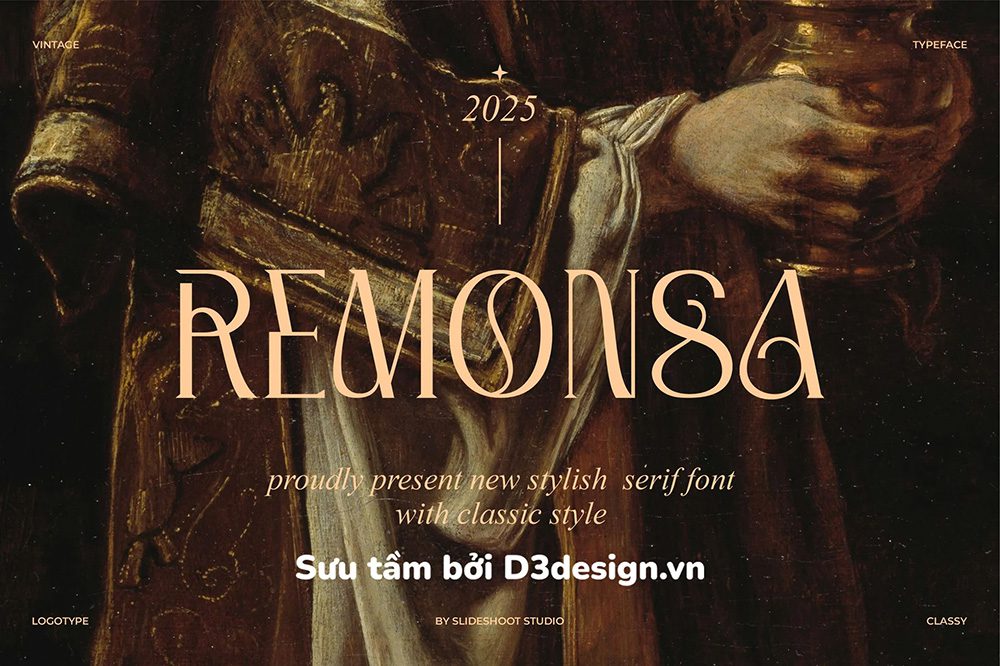
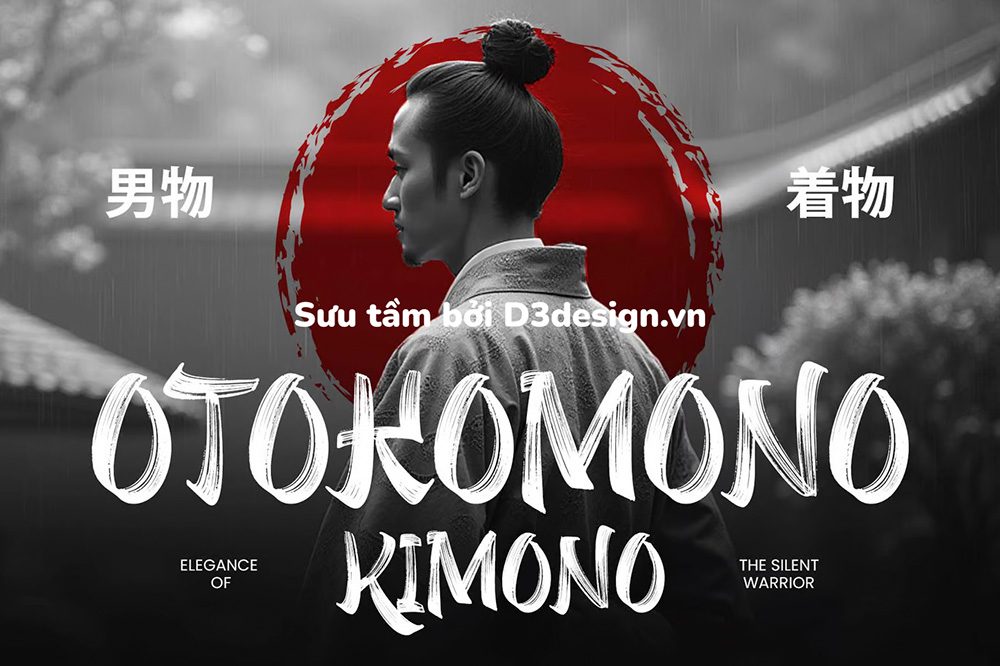
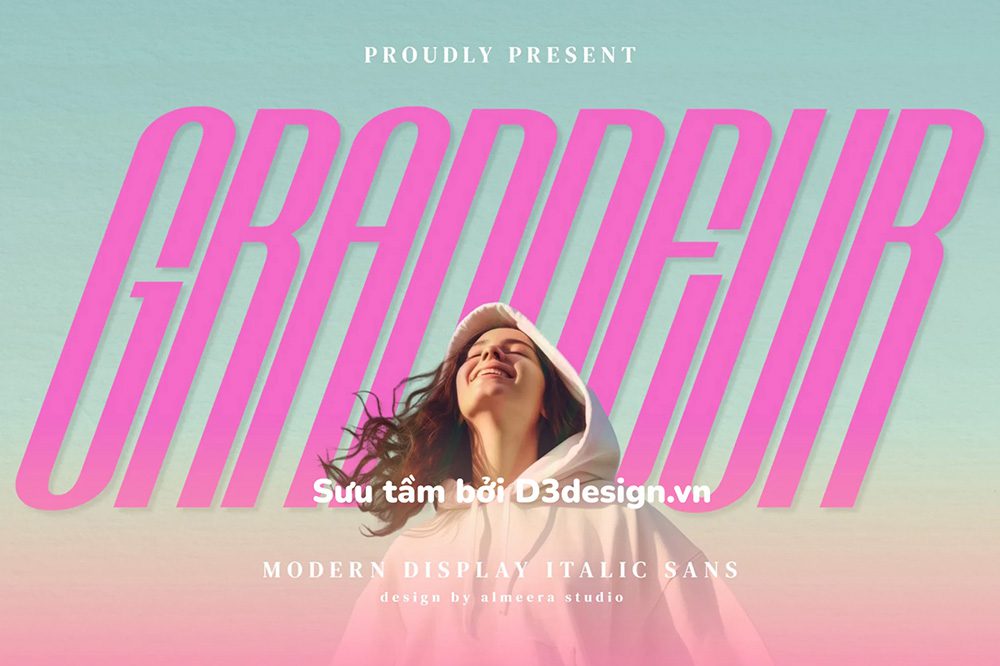
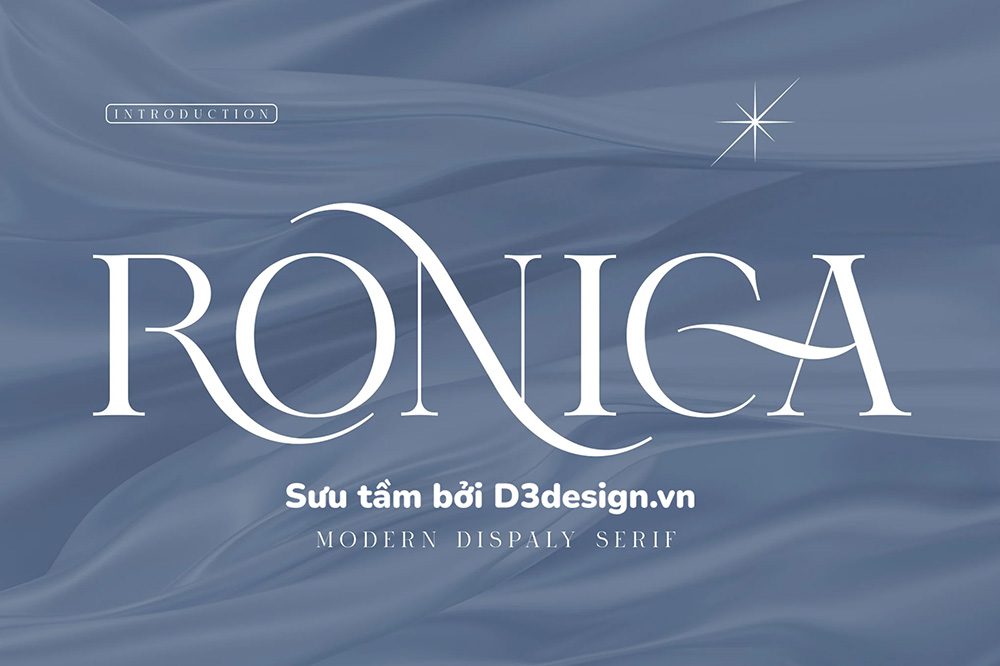
- Link download : TẢI FONT CHỮ ĐẸP
- Password : d3design.vn
Kết Luận
Font chữ là tài nguyên không thể thiếu đối với bất kỳ designer nào. Một bộ font đẹp, đa dạng và dễ sử dụng sẽ giúp quá trình thiết kế trở nên nhanh chóng, sáng tạo và chuyên nghiệp hơn. Việc Tải Font Chữ miễn phí là lựa chọn phù hợp để mở rộng kho tài nguyên cá nhân, đặc biệt với những ai thường xuyên thiết kế poster, banner, logo, bài đăng mạng xã hội hoặc ấn phẩm truyền thông.
Tuy nhiên, designer nên lựa chọn font một cách có chọn lọc, ưu tiên khả năng đọc, tính thẩm mỹ, hỗ trợ tiếng Việt và giấy phép sử dụng rõ ràng. Khi biết kết hợp font chữ đúng cách, mỗi thiết kế sẽ trở nên nổi bật hơn, truyền tải thông điệp hiệu quả hơn và tạo được dấu ấn riêng trong mắt người xem.